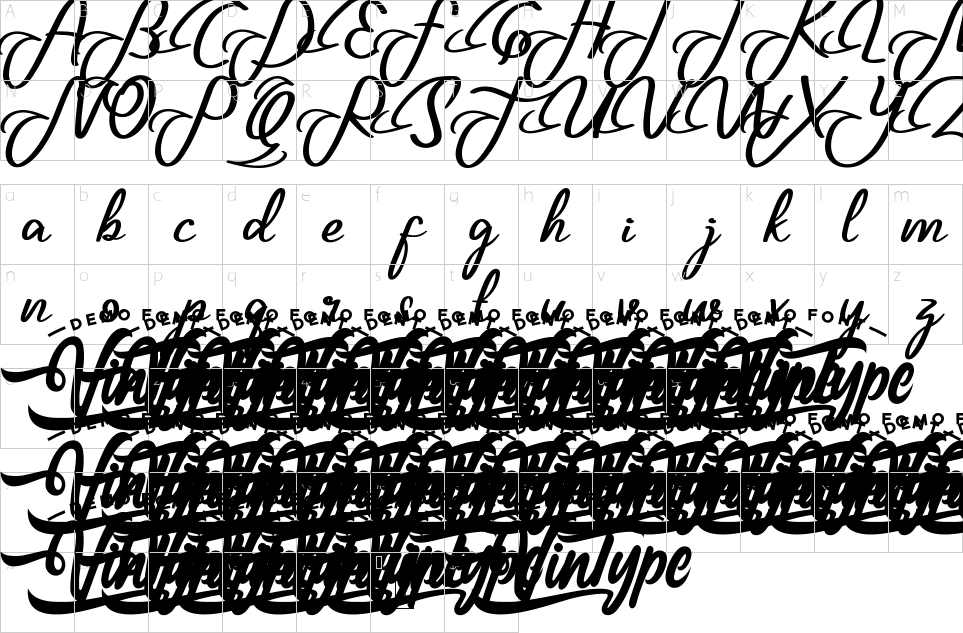
A fonte Mading é um belo complemento para a decoração de textos em seu site ou app. Desenhada por vintype, essa elegante fonte já foi baixada mais de 2.745 vezes. Ideal para estilos minimalistas e contemporâneos, a Mading é uma escolha perfeita para os designers que procuram uma fonte que combine beleza e funcionalidade. Ainda não testou essa fonte? É hora de dar uma olhada e ver por si mesmo como ela pode dar um toque especial em suas páginas. Com Mading, você pode adicionar um toque de sofisticação e modernidade aos seus design, sem comprometer o conforto visual e a legibilidade que tanto prezamos.